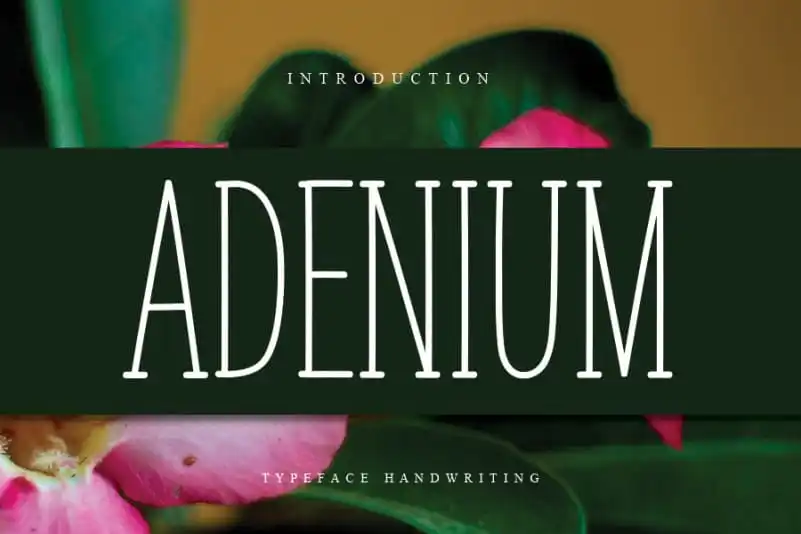
A ADENIUM Display Font é uma fonte à mão escrita encantadora que traz aos seus projetos uma atmosfera única e pessoal. Ideal para estilos de design como paredes decorativas, convites de casamento, postagens nas redes sociais, logotipos, embalagens de produtos, rótulos, fotografias ou até mesmo marcas d’água. Com seu estilo retrô perfeito, a ADENIUM Display fonte torna-se uma escolha ideal para uma variedade impressionante de aplicações gráficas, como se fosse o complemento perfeito ao seu design. Descubra por si só a forma elegante e versátil que esta fonte adquire quando aplicada à sua próxima peça visual.